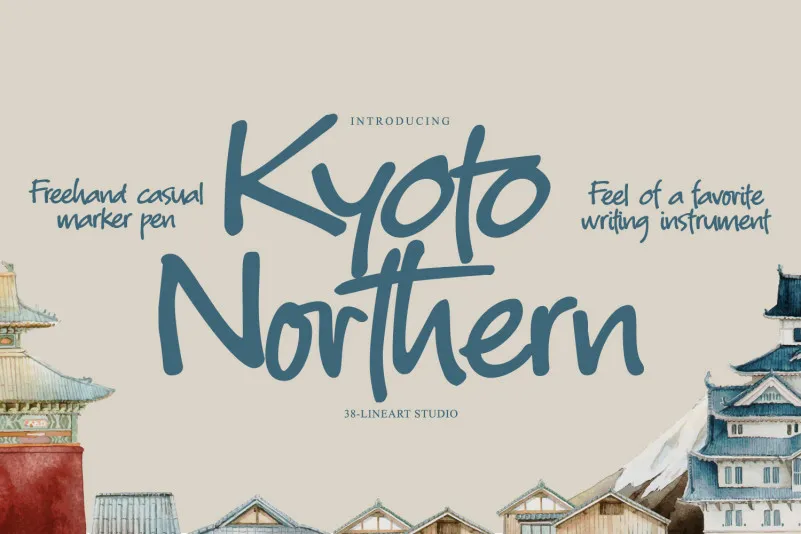
Kyoto Northern Handwritten Font – Download Grátis
A fonte “Kyoto Northern Handwritten Font” é uma escolha perfeita para quem busca transmitir elegância e sofisticação em qualquer aplicação visual. Ela se destaca por sua naturalidade única, tornando-a ideal não apenas para identidades de marca, mas também para pacotes comerciais, banners na web, headlines e até mesmo cartões de visita. Seu estilo delicado e autêntico permite que você personalize suas mensagens de maneira personalizada e envolvente, criando uma conexão imediata com seu público-alvo. Esta fonte é uma ótima adição para qualquer designer que busca algo diferenciado e extremamente agradável ao olhar para complementar seus projetos digitais e impressos.